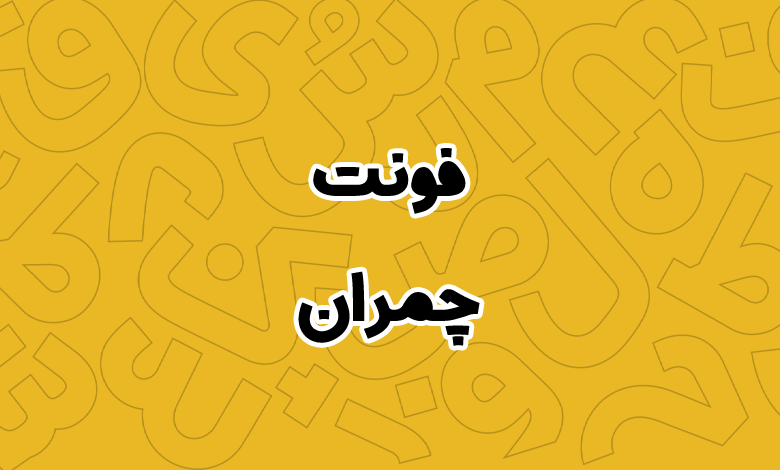
فونت چمران (Chamran)
فونت چمران (به انگلیسی: Chamran) از دیگر فونتهای رایگان به سبک سنس است که میتوانید از آن برای تیترنویسی استفاده کنید. این فونت ظاهری فانتزی در بخش چشمی حروف دارد که همگی توپر هستند که ساختاری نمایشی به آن داده است.
فونت چمران توسط محمد عموئی با یک وزن معمولی Regular طراحی شده، اما ضخامت حروف نسبتا توپر است که ظاهری بولد به این قلم داده است. از این فونت میتوانید در متون کوتاه و بلند استفاده کنید، اما بهترین کاربرد آن برای تیترنویسی در متون کوتاه است.
فونت چمران از زبانهای فارسی، عربی و انگلیسی پشتیبانی میکند. این قلم سنس دارای ظاهری نسبتا ایتالیک بهنظر میرسد و تمامی حروف در بخش منحنیها دارای ظاهری خاص هستند که آن را نمایشیتر و دوستانهتر کرده است.
اگر به دنبال فونتی برای استفاده در عنوان جلد کتاب هستید یا میخواهید فونتی صمیمی داشته باشید که برای چاپ روی بنر و بیلبوردهای تبلیغاتی از آن استفاده کنید این فونت باز هم مناسب کار شماست. بهویژه در اندازههای بزرگ که خود را بهتر نشان میدهد.